Las mejores fuentes para tablas que deberías usar
Publicado: 2023-08-08Está cocinando una mesa, no con tenedores y cuchillos, sino con datos, hechos y cifras. No es ningún secreto que la verdadera especia en esta receta digital es la fuente que usa. Pero entonces, ¿cuáles son las mejores tipografías para tablas?
imagina ,
Tienes números, encabezados, texto diminuto, todo empaquetado en ese pequeño espacio. Entonces, ¿cómo haces que todo sea legible, pero sabroso? Eso es lo que estamos aquí para servir.
No estamos simplemente tirando alrededor de Arial y Times New Roman aquí. Estamos hablando de fuentes gourmet que harán que sus mesas destaquen con claridad y estilo. El tipo de fuentes que hablan a los ojos.
Cada celda de tu tabla tiene una voz. Lo vamos a amplificar. Vamos a hacer cantar cada dígito y letra. Encendamos la parrilla de diseño y hagamos de sus mesas el plato principal que todos quieren consumir.
Las mejores fuentes para tablas
roboto
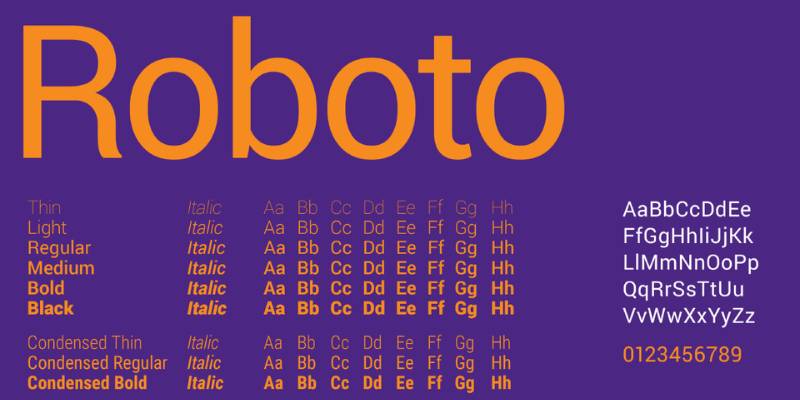
Bueno, Roboto es una obviedad, de verdad. Es una fuente que respira sencillez y claridad. Para las tablas, es un sueño, ya que ofrece líneas nítidas y fácil lectura. La fuente tiene sus raíces en las formas geométricas, lo que garantiza el equilibrio y la armonía. Una mesa puesta en Roboto es como una cocina bien organizada; todo está en su lugar correcto.
Lato
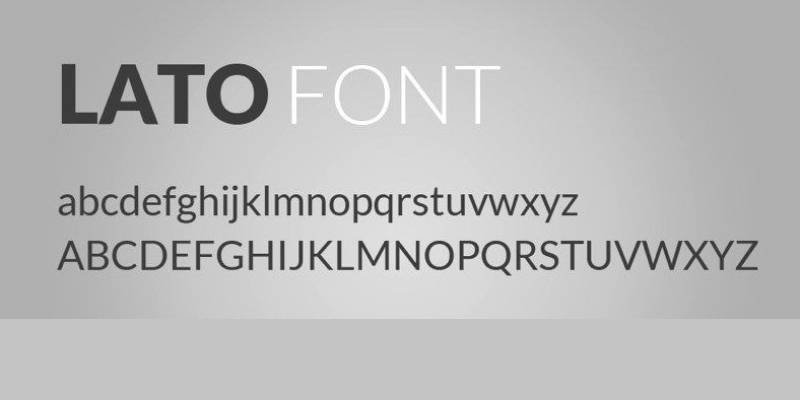
Volviendo a Lato , encontramos una fuente elegante y cálida. La belleza de Lato radica en sus detalles semirredondeados, que dan a las mesas un ambiente agradable. A pesar de esta calidez, Lato conserva un sentido de profesionalismo. Es como el tipo genial de la oficina que sabe cómo hacer el trabajo.
abrir sans
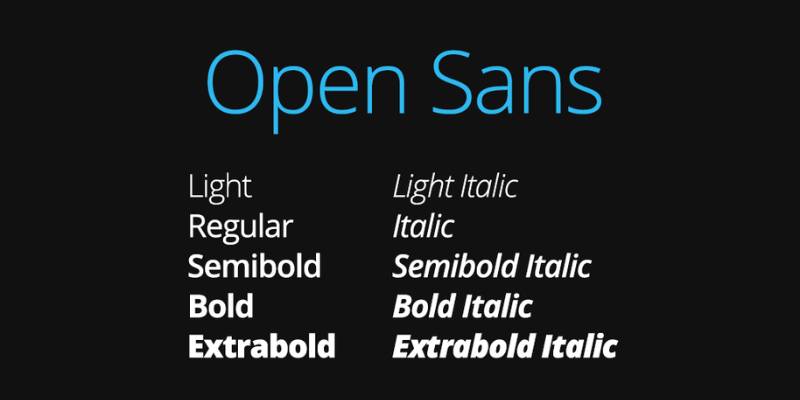
Open Sans es como ese par de jeans confiables a los que siempre recurres. Optimizada para interfaces de impresión, web y móviles, esta fuente es tan versátil como parece. Para las mesas, Open Sans es una combinación perfecta. Garantiza una fácil lectura y una apariencia limpia que no envejece.
Fuente Sans Pro
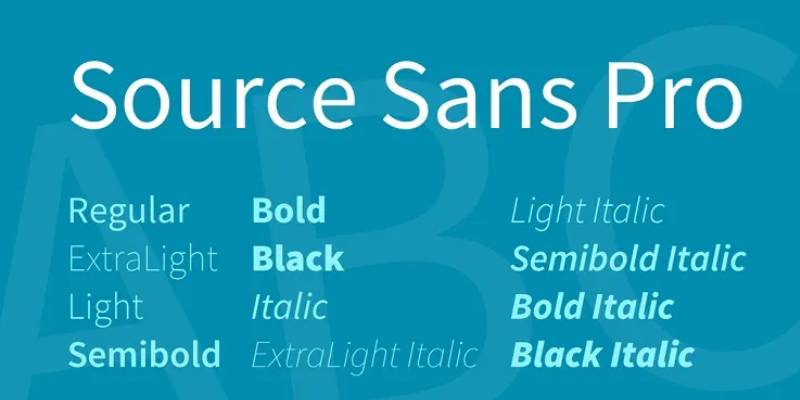
Adelante a Source Sans Pro . Aquí hay una fuente que nació para espacios digitales. Su legibilidad y variedad de pesos lo convierten en una opción fantástica para mesas. Piense en Source Sans Pro como una navaja suiza, lista para adaptarse y hacer que sus datos brillen.
Noto Sans
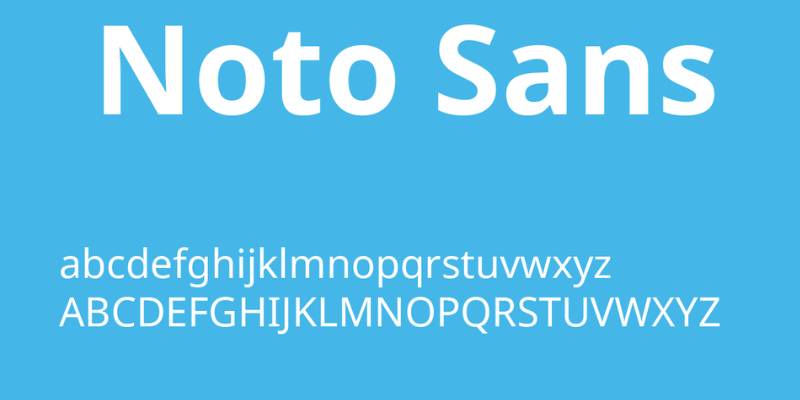
Saluda a Noto Sans . Diseñado con el objetivo de admitir todos los idiomas con una apariencia armoniosa, es una fuente que grita inclusión. Las mesas vestidas con Noto Sans son agradables a la vista y ricas en carácter. Es como un crisol de culturas, pero para fuentes.
verdana
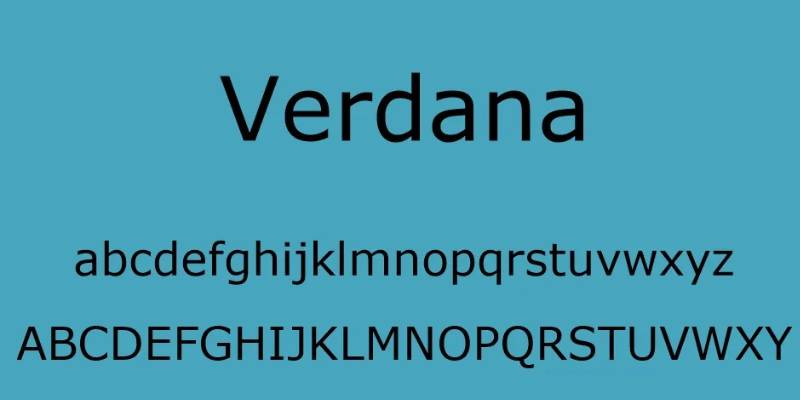
Ah, Verdana . Un viejo pero un oro. Es conocido por sus letras anchas y alta legibilidad incluso en tamaños pequeños. Si está diseñando tablas que requieren texto pequeño, Verdana es su mejor opción. Es el jugador veterano del equipo, siempre entregando cuando más importa.
Georgia
A continuación, Georgia . Una fuente serif que es perfecta para aquellos que buscan un ambiente clásico. Su legibilidad es excelente, y los pequeños trazos decorativos aportan un toque de elegancia a tus mesas. Georgia es como una gran biblioteca, sofisticada pero accesible.
Tahoma
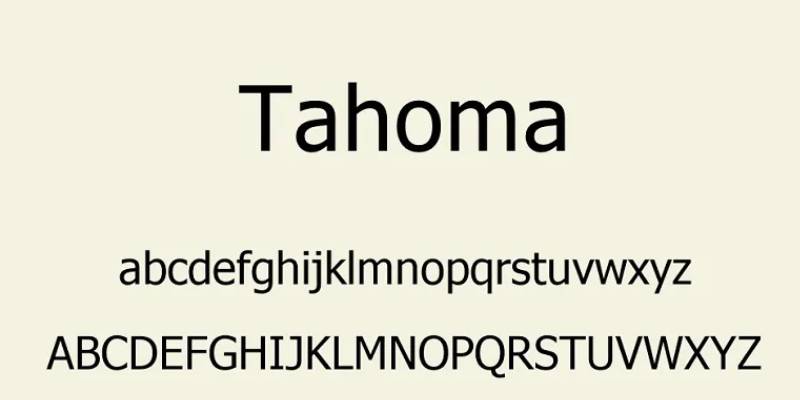
Te presentamos Tahoma . Aquí hay una fuente que equilibra el espacio reducido entre letras con una alta legibilidad, creando una apariencia fresca y limpia. En forma de mesa, Tahoma brinda una estética nítida que es puro placer para los ojos. Piense en ello como el aliento fresco a menta del mundo de las fuentes.
innumerables profesionales
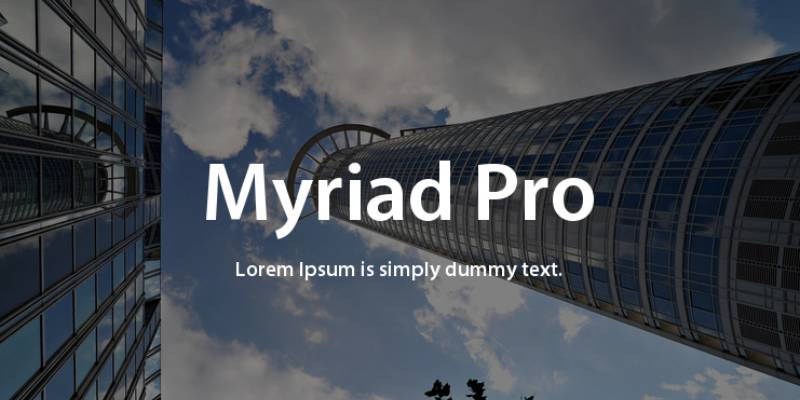
Myriad Pro entra en escena con su aspecto amigable y abierto. Su tono profesional, junto con un toque de calidez, lo hace perfecto para el diseño de mesas. Myriad Pro es como ese amigo burbujeante que también tiene su vida en común.
campana gótica
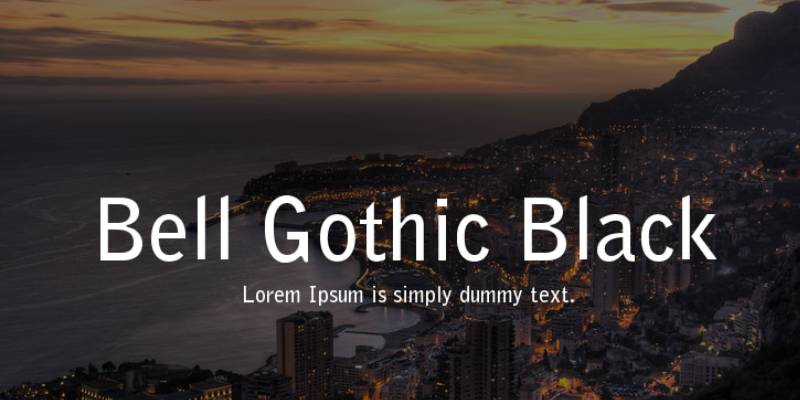
Bell Gothic es bastante innovador. Diseñado originalmente para guías telefónicas, es excelente para cualquier mesa que necesite mostrar información de manera concisa. Bell Gothic es el ícono de la moda en el mundo de las fuentes, siempre yendo un paso por delante.
Helvética
Ninguna lista de fuentes estaría completa sin Helvetica . Es simple, limpio y súper versátil. Es el vestidito negro de las fuentes, queda genial en cualquier situación, incluidas las mesas.
Arial
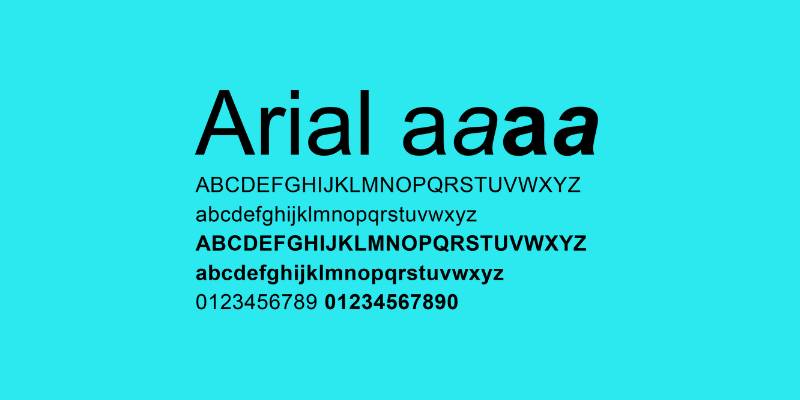
Conoce a Arial , la prima de Helvetica. Es una opción popular por una razón: es familiar, amigable y facilita la lectura. Con Arial, sus mesas están en buenas manos. Es el alimento reconfortante de la familia tipográfica.
pt sans
Saluda a PT Sans . Es una fuente que se siente moderna pero arraigada en la tradición, con sus estilos humanista y grotesco. PT Sans trae un giro emocionante a las mesas, como una especia que agrega un nuevo sabor.
exo
Aquí viene exo . Esta fuente toma el futuro en sus propias manos, con un ambiente tecno que se siente fresco e innovador. Las mesas decoradas con Exo parecen sacadas de una película futurista de ciencia ficción. Abróchate el cinturón, es una fuente que te lleva de paseo.
El tamaño también importa. Asegúrese de que su texto sea agradable a la vista. ¿Y color? Es la guinda que une todo.